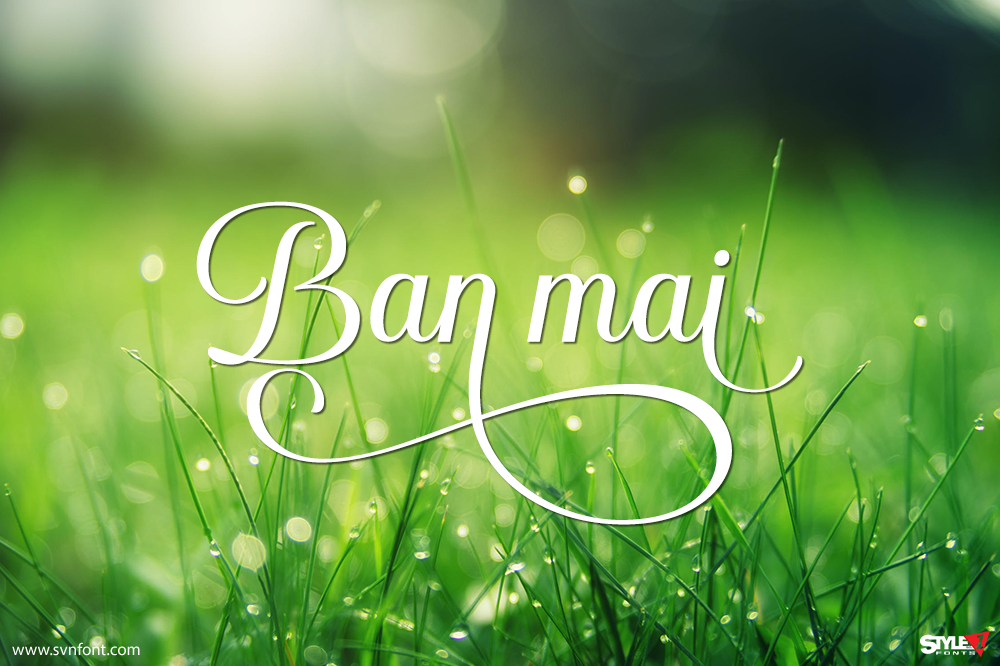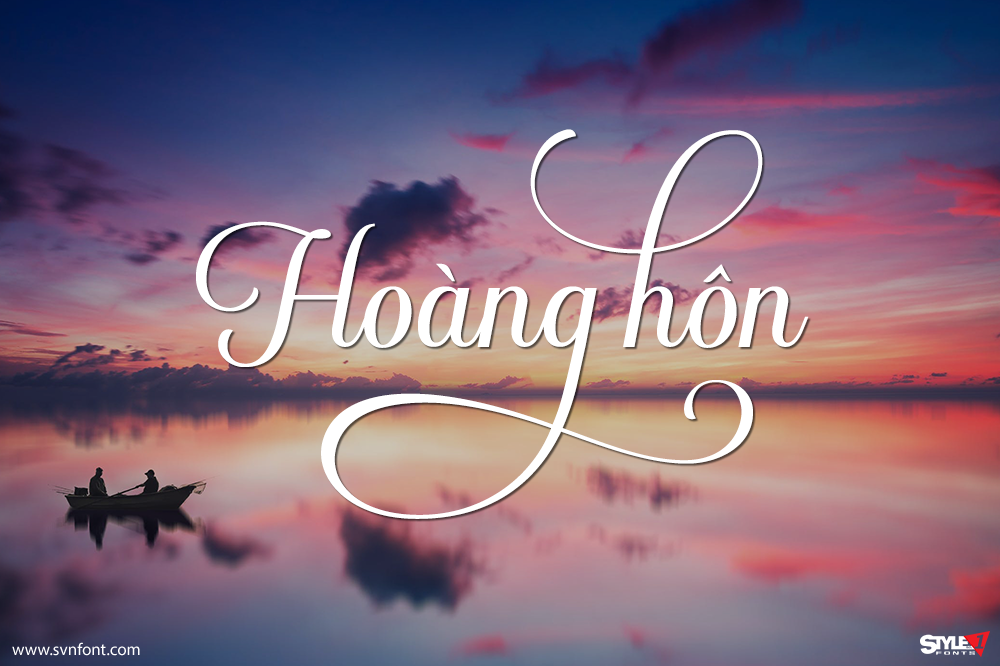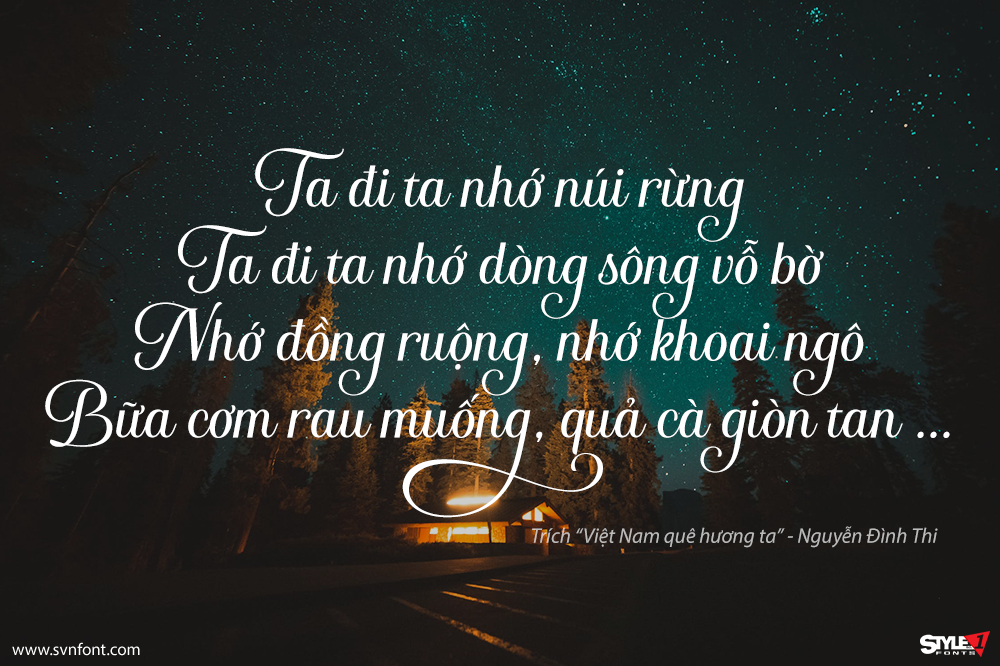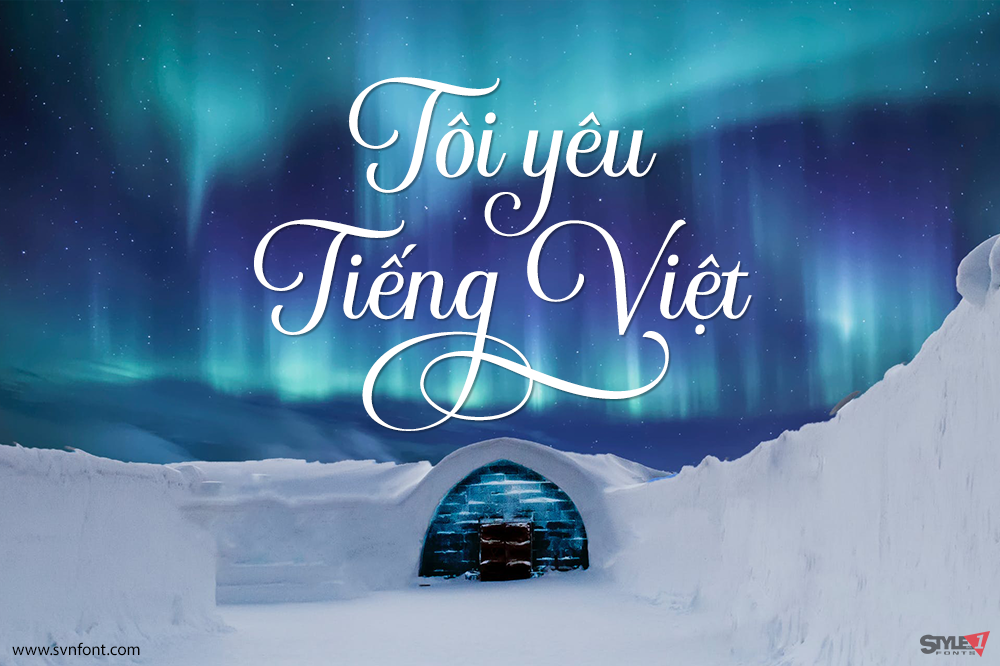
Santillana Daughter là một font script nhẹ nhàng và tinh tế, toát lên vẻ thanh lịch và sang trọng. Typeface này được thiết kế dành riêng cho những ai tìm kiếm một diện mạo tươi mới, đẹp mắt cho các dự án của mình.
Font được PUA encoded, giúp bạn truy cập dễ dàng toàn bộ glyph và swash mà không cần phần mềm hỗ trợ đặc biệt, rất thuận tiện cho quá trình sáng tạo.
Nhà thiết kế: Muksalmina
Nhà phát hành: Mercurial Studio